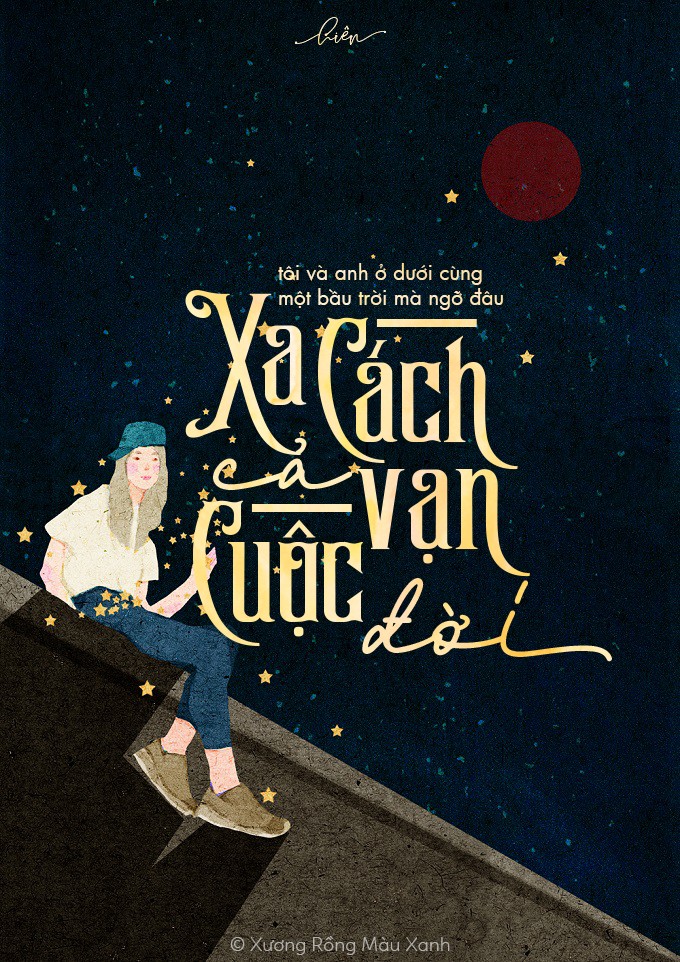
Font Việt hóa MTD Blaze Glory – Bộ Phông Chữ Đẳng Cấp Cho Thiết Kế
Trong thế giới đồ họa hiện đại, việc lựa chọn Font Chữ phù hợp đóng vai trò then chốt để truyền tải thông điệp hiệu quả. Font Việt hóa MTD Blaze Glory nổi lên như một sự lựa chọn hàng đầu cho các nhà thiết kế yêu thích phong cách mạnh mẽ nhưng không kém phần tinh tế. Với đường nét được trau chuốt tỉ mỉ, bộ phông này giúp các ấn phẩm truyền thông trở nên chuyên nghiệp và bắt mắt hơn bao giờ hết.
Khám phá đặc điểm nổi bật của Font Việt hóa MTD Blaze Glory
Phong cách thiết kế độc đáo và hiện đại
MTD Blaze Glory sở hữu cấu trúc hình khối vững chãi cùng những nét cắt sắc sảo, tạo nên cảm giác hiện đại và đầy năng lượng. Đây là kiểu chữ lý tưởng để ứng dụng vào các tiêu đề tạp chí, bìa sách hoặc các dự án xây dựng thương hiệu cá nhân. Sự cân đối giữa các ký tự giúp văn bản giữ được độ thoáng, dễ đọc ngay cả trên màn hình kỹ thuật số lẫn bản in truyền thống.
Khả năng tương thích và hỗ trợ tiếng Việt hoàn hảo
Ưu điểm lớn nhất của phiên bản này chính là việc đã được tối ưu hóa dấu tiếng Việt một cách chuẩn xác. Người dùng không còn phải lo lắng về lỗi hiển thị hay các dấu thanh bị lệch vị trí. Điều này đặc biệt hữu ích cho các bạn học sinh và giáo viên khi soạn thảo giáo án điện tử hoặc thiết kế bài thuyết trình sinh động, giúp nội dung bài học trở nên gần gũi và lôi cuốn hơn đối với người xem.
Ứng dụng Font Việt hóa MTD Blaze Glory trong thực tế
Bộ phông chữ này thường xuyên được sử dụng trong các sản phẩm quảng cáo, poster sự kiện và thiết kế áo thun. Nhờ tính linh hoạt cao, bạn có thể dễ dàng kết hợp nó với nhiều phong cách khác nhau từ cổ điển đến tương lai. Để có những trải nghiệm thiết kế tốt nhất, hãy tải ngay Font Miễn Phí, Font Việt Hóa, Font Việt hóa MTD Blaze Glory để sáng tạo nên những tác phẩm nghệ thuật mang đậm dấu ấn cá nhân và chuyên nghiệp nhất cho dự án của mình.